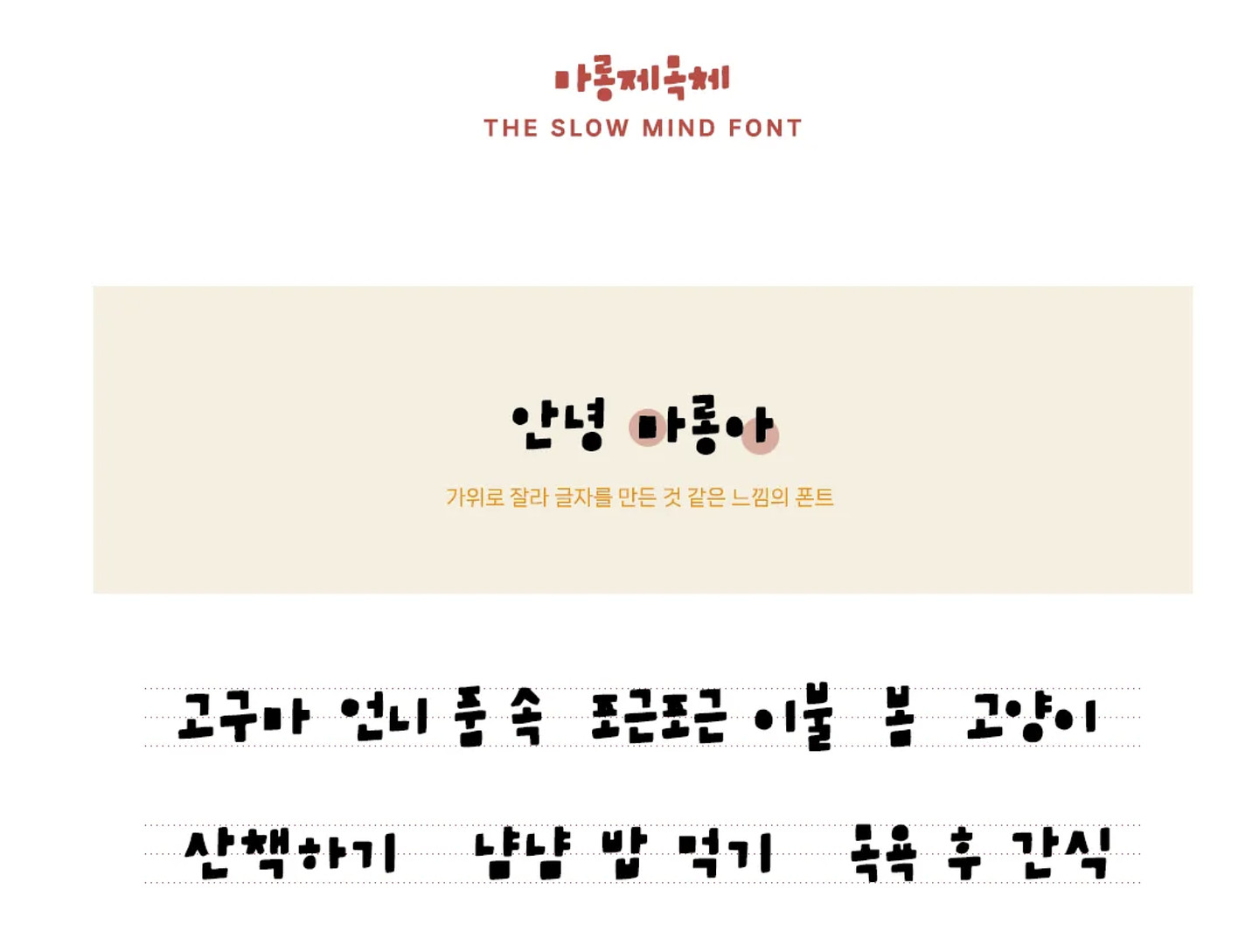
폰트가 아니라
손글씨로 보입니다! 비슷한 폰트로는 마롱제목체가 있습니다! https://smartstore.naver.com/theslowmind/products/8242052472
전에 작업하면서 봤던 폰트를 대략적인 기억으로 그려봤는데 이 형태와 가장 가까운 폰트가 있을까요? 제 기억이 맞다면 잠깐 일하던 곳에서 산돌 클라우드가 깔려있던 것 같습니다.